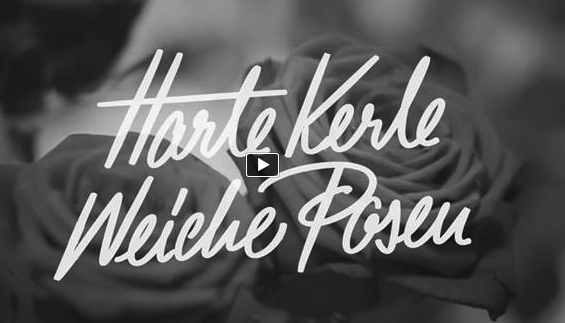
Schriftsuche again :-)
ich suche wieder eine Schrift und zwar die Handschrift im angehängten Foto.
Hat jemand eine Ahnung?
Es gibt Leute, die pinseln so etwas aus dem Handgelenk 100 mal schneller, als sie für die Suche nach einem passenden Font einsetzten müssen, Mir erscheint das auch eher nach einer gekonnten und gut eingeübten Handschrift. Ich schaue hier nicht nur auf die Buchstaben selbst, wie auchauf die Verbindungslinien in der Schreibschrift, das währe nur mit ausgefeiltestem OpenType hin zu bekommen.